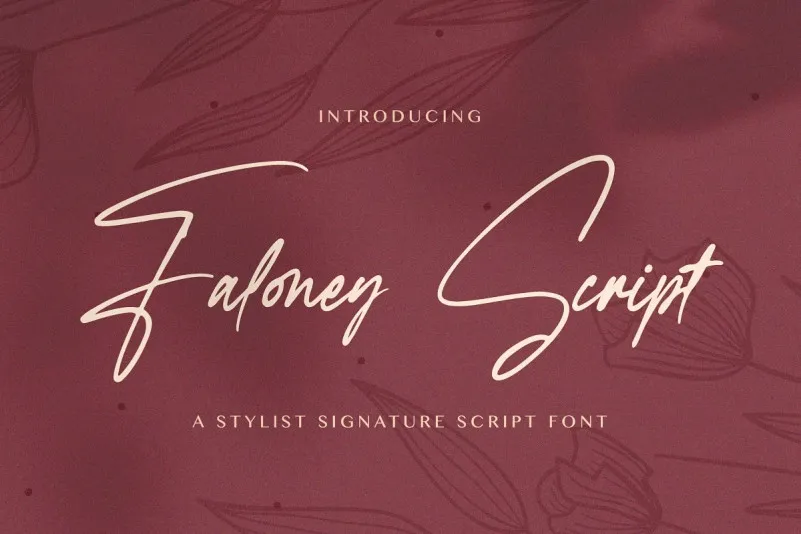
A ‘Faloney Script Font’ é uma elegante e fina tipografia script que transmite sofisticação e elegância. Com seus caracteres belamente equilibrados, ela se destaca como a escolha perfeita para projetos criativos de diversos estilos. Seja em um design minimalista ou mais elaborado, essa fonte trará uma sensação única e encantadora que certamente fará seu trabalho brilhar. Adicione ‘Faloney Script Font’ a seus próximos projetos e observe como ela transforma sua inspiração em realidade visível, tornando-os ainda mais impactantes e memoráveis.